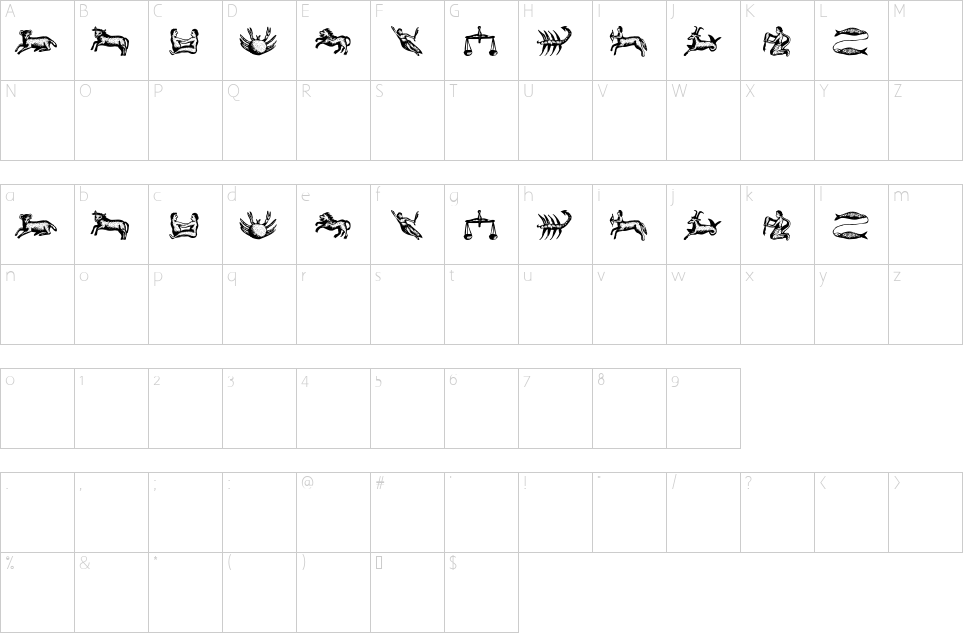
Astrologicus é uma fonte de graça desenvolvida pelo designer Vladimir Nikolic. Ela foi projetada para oferecer um estilo distintivo e versátil, adequada para criar designs variados, desde postagens de redes sociais até materiais de marketing. Seu design elegante e fácil de ler torna-a uma opção popular para designers e freelancers que buscam fontes confiáveis para seus projetos. Com um download de mais de 4.297 vezes, Astrologicus prova ser uma fonte de qualidade que vale a pena experimentar. Se você está procurando uma fonte de graça para seus projetos, Astrologicus pode ser uma ótima escolha.